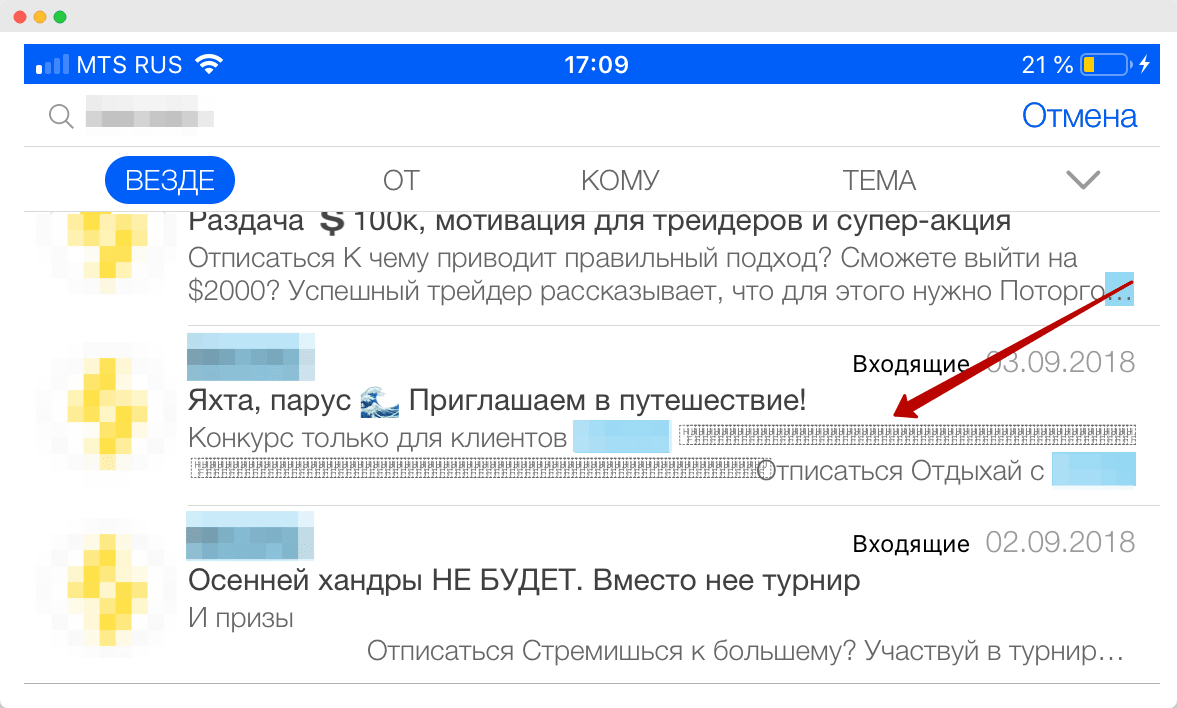
А как насчёт того, чтобы проигнорировать стили темы и использовать в ней декоративные шрифты? Это привлекает внимание:
Как сделать красивый шрифт в теме письма (да, так можно!) за 2 минуты при помощи ???????
Как это сделать
Чтобы поставить новый шрифт, не нужно использовать CSS-стили или атрибуты HTML. Поменять шрифт можно с помощью Юникода.
Юникод — стандарт кодирования символов. Когда мы используем эту кодировку, текст превращается в набор символов с определёнными характеристиками. Примеров использования Юникода много: например, эмоджи — часть этой кодировки.
Увы, но вариантов для креатива на кириллице, как волос на голове лысого из «Браззерс» — катастрофически мало. У большинства кириллических знаков просто нет аналогов в Юникоде.
С латиницей дела обстоят лучше. Как это можно использовать:
- Выделить название бренда, если оно пишется на английском.
- Выделить слово в теме письма, если оно состоит из универсальных букв: А, В, Е, К, М, Н, О, Р, С, Т, У, Х. У этих знаков есть аналоги и в латинице, и в кириллице. При должном воображении из 12 букв можно придумать очень много слов.
Как вы понимаете, несмотря на ограничения, выкрутиться можно.
Как конвертировать текст в символы Юникода
Делюсь несколькими сервисами, которыми пользуюсь сам.
LINGOJAM. Этот сервис понравился мне больше всего. LINGOJAM легко пользоваться: вставляем текст в левое окно, а справа получаем разные варианты с символами Юникода.
- Unicode® Character Table. Просто таблица с распространёнными символами Юникода.
- Messletters. Помимо смены шрифта через Юникод в сервисе можно кастомизировать текст верхним и нижним регистром.
- Coolsymbol. Аналог LINGOJAM, но без поддержки кириллицы.
Какие платформы поддерживают
Приём работает в таких почтовых приложениях:
- Gmail.
- Mail.ru.
- Яндекс.Почта.
- Yahoo.
- Outlook/Hotmail.
- UKR.NET.
Как реагируют спам-фильтры
Я проверил письмо с Юникодом в сервисе Mail-tester. Декоративные шрифты никак не влияют не репутацию email:
На что обратить внимание
- Не все сервисы рассылок поддерживают Юникод в теме письма и имени отправителя. Но если вы верстаете вручную, то как минимум в прехедер всегда можно поместить текст с Юникодом. И да, UniSender поддерживает Юникод в теме, имени отправителя и прехедере.
- Всегда проверяйте как отображается Юникод в различных почтовых клиентах, браузерах и операционных системах. Например, некоторые скрытые символы, которые заменяют пробел, отлично отображаются на Windows, но вылезают в виде непонятных закарючек на macOS и iOS.
- Используйте Юникод с умом. Достаточно немного переборщить и вместо темы получится нечитабельная крипота.